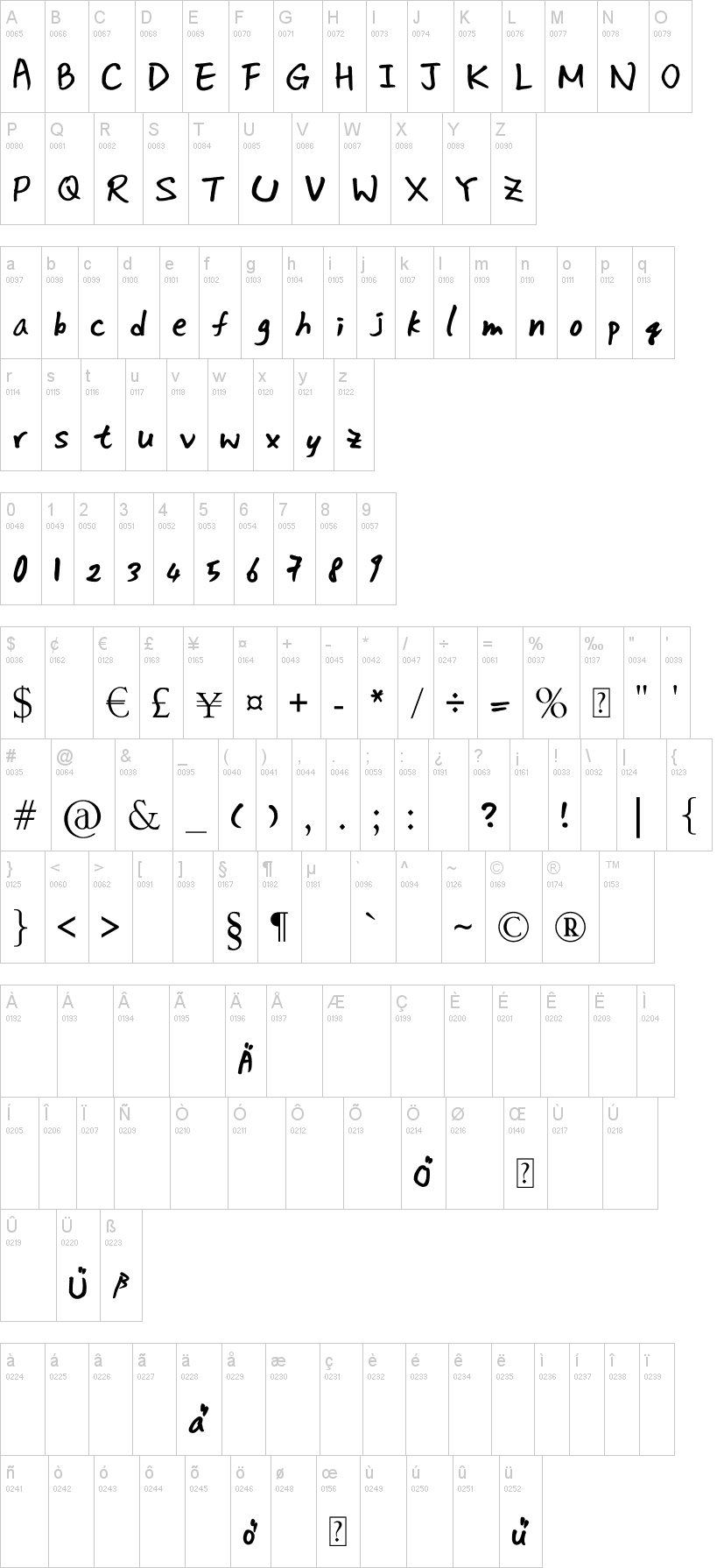
Da Silvano
Da Silvano 是一种手写风格的书法字体,它的字母线条流畅、优美,可以给文字带来一种优雅、艺术的感觉。这种字体的笔画有些类似于意大利书法风格,所以它在一些意大利风格的设计中也比较常见。Da Silvano 字体可以用于各种场合,例如书信、卡片、海报、广告、设计等,给文字带来一种独特的风格和美感。
Da Silvano是一款非常不错的手写艺术字体,具有很好的视觉感,适合于文化类的宣传设计、商业类品牌的广告和产品包装设计以及个性化文字排版等较多场景。
Da Silvano字符映射图